| |  | |  Met trots presenteert de Dutch Type Library het nieuwe, uiterst veelzijdige schreeflettertype dtl Valiance, ontworpen door de bijzonder getalenteerde en gelauwerde Finse letterontwerpster Hanna Hakala. De productie van dtl Valiance begon in 2007, toen Hanna haar mastertitel behaalde aan de fameuze TypeMedia opleiding van de Koninklijke Academie van Beeldende Kunsten in Den Haag (kabk). Na tien jaar van polijsten, testen, herziening en verbetering is dtl Valiance nu verkrijgbaar in alle actuele fontformaten.
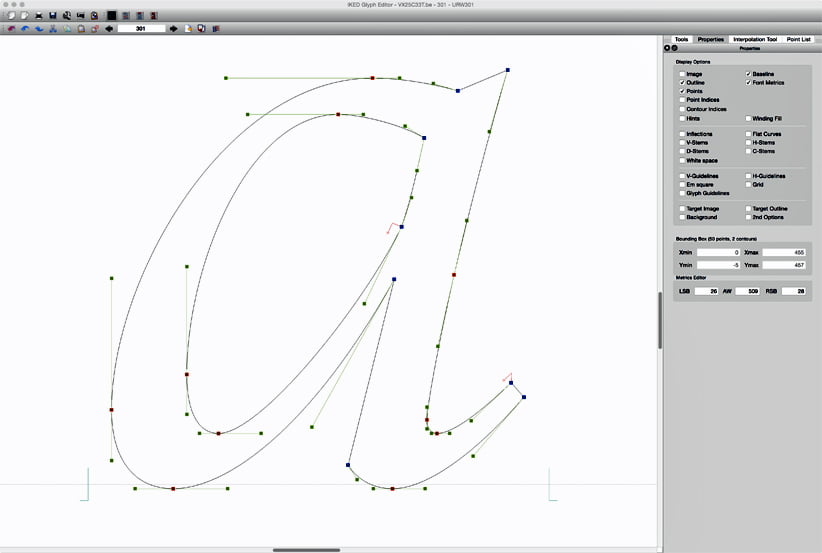  dtl Valiance is geschikt voor iedere denkbare typografische toepassing: van tijdschriftvormgeving tot website-ontwerp en van boektypografie tot huisstijlontwikkeling. Dit unieke lettertype kan worden toegepast door ontwerpbureaus en in kantooromgevingen. Haar klassieke, tijdloze, stevige doch elegante ontwerp maken dtl Valiance erg geschikt voor gebruik op hoge resolutie, zoals laserbelichters, maar ook voor apparatuur met een relatief lage resolutie, zoals computerschermen en laserprinters. De karaktersets die dtl Valiance ondersteunt, omvatten alle West-, Oost-, en Centraal-Europese talen, naast Cyrillisch (inclusief Bulgaarse en Servische varianten).
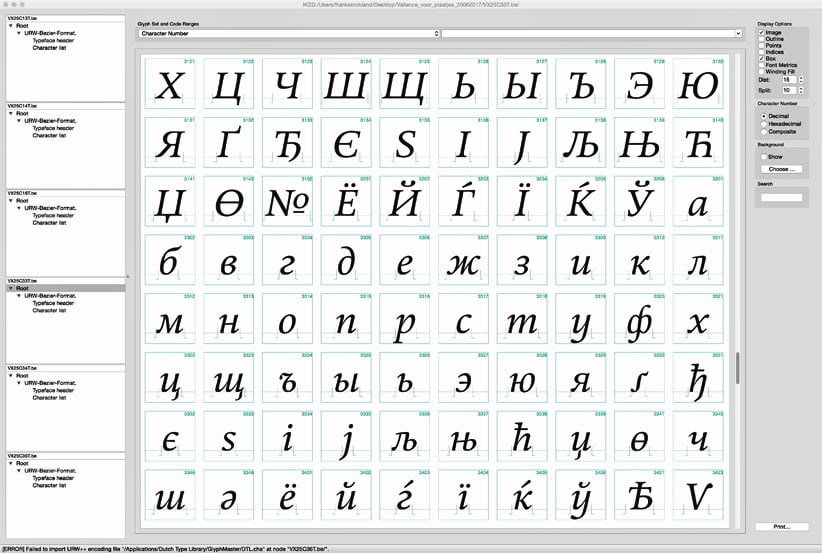
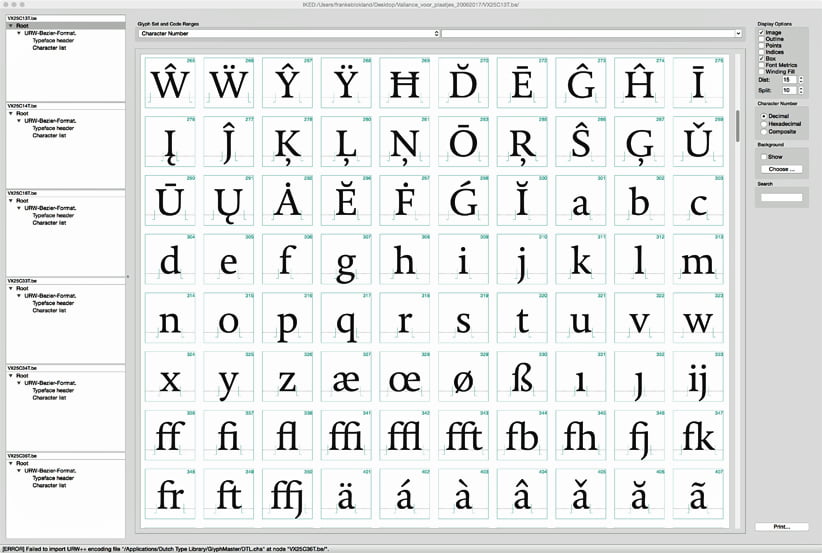  Speciaal voor de goody bag van de ATypI Amsterdam conferentie in 2013 publiceerde de Dutch Type Library Notes on the Design of dtl Valiance Cyrillic. In dit boekje presenteert Hanna Hakala een verzameling van aantekeningen die zij maakte tijdens het ontwerpproces van dtl Valiance. Deze beknopte publicatie voorziet letterontwerpers met duidelijke richtlijnen voor het ontwerpen van Cyrillische karakters en bevat verder historische achtergrondinformatie. Vier jaar geleden waren de reacties op Notes on the Design of dtl Valiance Cyrillic erg positief, zoals deze van een manager van ’s werelds grootste fontdistributeur: ‘You produced an excellence type specimen and story on Cyrillic letterforms. It is wonderfully done, and a true pleasure to read and absorb.’
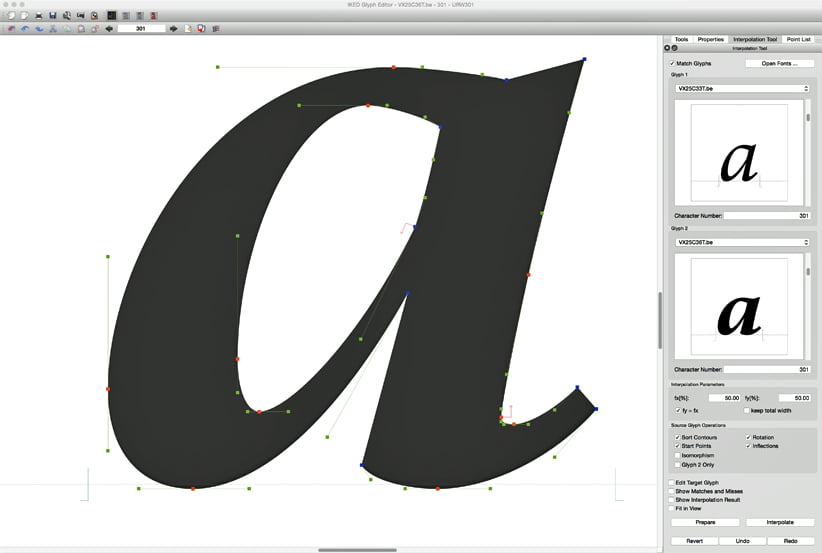
Bovenop al deze functionaliteit komt de optie om OpenType Layout features files (met afdko syntax) te im- en exporteren. Bij het importeren vindt subsetting plaats, wat inhoudt dat features die niet overeenkomen met de karakterset van een font worden verwijderd. Dit is mogelijk doordat de programmeurs van urw++ de functionaliteit van de afdko hebben uitgebreid.
dtl OTMaster is verkrijgbaar voor Mac os X –versie 6 is volledig geoptimaliseerd voor Retina– Windows, en Linux. Alle downloads bevatten de otm handleiding in pdf formaat. Een gebruikerslicentie voor otm 6 kost normaal € 255,– maar wordt tot 1 juni 2016 geleverd met 25% korting, oftewel €191,25 via dtl’s FontTools Shop. Gratis ‘Light’ (3.6) versies zijn te downloaden van de FontMaster website.   Op 6 februari 2007 verschenen zes regionale kranten van uitgeverij Wegener voor het eerst in tabloid formaat (zie ook dit nieuws. Een zevende editie werd sinds eind 2006 al gedrukt op het kleinere formaat. De overgang verliep technisch soepel op het Hermes opmaaksysteem en de nieuwe tabloids werden overwegend positief ontvangen.
Voorafgaand aan de omzetting naar tabloid formaat hadden grafisch ontwerpers van Wegener, merkendeskundigen en lettertypenexperts van de Dutch Type Library meer dan een jaar samengewerkt om de vormgeving van de zeven edities te vernieuwen. Tezamen vormen deze edities met zo’n miljoen tabloids per dag één van de grootste kranten in de wereld en daardoor heeft de vormgeving ervan behoorlijk wat impact. Alle toegepaste lettertypen werden ontwikkeld door de Dutch Type Library. De nieuwe lettertypen werden speciaal ontwikkeld voor toepassing in kranten: dtl Porta News werd ontworpen door de Kroatische letterontwerper Nikola Djurek, en dtl Caspari News en dtl Albertina Headline werden ontwikkeld door de dtl Studio. Voor sommige redactionele stukken werd dtl Albertina toegepast. Voorafgaand aan het herontwerp vonden verschillende intensieve leesbaarheidsonderzoeken onder groepen lezers plaats. De uitkomst was een klare overwinning van dtl Porta op Swift, het lettertype dat totdantoe het meest was toepast door uitgeverij Wegener. dtl’s oprichter Frank E. Bloklend ontwierp de zeven nieuwe krantentitels. Uitgangspunt daarbij was de standaardisatie, modernisering en technische verbetering van de bestaande krantentitels, zonder dat de indentiteit te veel werd veranderd. Dat laatse was een voorwaarde van uitgeverij Wegener, dat daarmee tegemoetkwam aan de voorkeuren van de ‘lokale’ redacteuren en journalisten. In 2012 werd het ontwerp van de Wegener-dagbladen nog verder geoptimaliseerd. Een special daartoe gevormde werkgroep, geleid door grafisch ontwerper Erik Gigengack en geadviseerd door krantenspecialist Mark Porter werkte in totaal zo’n driekwart van een jaar hieraan. Toentertijd waren dtl Caspari News en dtl Porta News al in gebruik, zoals hierboven gememoreerd, maar met beperkte sets van stijlen en gewichten voor de lopende tekst en kleinformaat koppen. Beide lettertypen werden uitgebreid met additionele fonts voor tekstformaat én met geheel nieuwe displayversies, die ind plaats kwamen van de dtl Albertina en dtl Albertina Headline fonts. Sommige van de nieuwe fonts worden nu ook door uitgeverij Wegener op het web toegepast in @font-face formaat. De eerste reacties van lezers en producenten van de Wegener-dagbladen op de nieuwe dtl ‘News’ lettertypen zijn erg enthousiast. De complete serie van dtl Caspari News en dtl Porta News fonts zijn nu ook beschikbaar voor de eindgebruikersmarkt en verkrijgbaar via dtl’s webwinkels. Een speciale letterproef op tabloidformaat, die oorspronkelijk geproduceerd was voor de goody bag van de ATypI Amsterdam 2013 conferentie, is op aanvraag verkrijgbaar bij de Dutch Type Library.    Op zaterdagavond 12 oktober 2013 vond het diner van de ATypI conferentie plaats in het sfeervolle Winter Garden restaurant van Grand Hotel Krasnapolsky in Amsterdam. Meer dan 300 conferentiegangers genoten van het uitstekend verzorgde buffet, dat was gesponsord door Adobe. Het hoogtepunt van de avond was de presentatie van de derde Dr. Peter Karow Award for Font Technology & Digital Typography (kortweg pka) aan Dr. Donald E. Knuth.
Grand Hotel Krasnapolsky in Amsterdam
Bij de ingang van het Winter Garden restaurant ontving iedereen een aandenken in de vorm van een 56 pagina’s dik boekje met als titel Digital Typography & Artificial Intelligence. Hierin beschrijft software-pionier Dr. Peter Karow, oprichter van het bedrijf urw Software & Type GmbH begin jaren zeventig en vooral bekend én beroemd vanwege het ikarus formaat, hoe digitale typografie het letterontwerpen en tekst-layout heeft beïnvloed. Het heeft de productie van fonts en het zetten van tekst compleet veranderd.
Dr. Knuth kreeg een staande ovatie van het ATypI-publiek. En zoals Nicole Miñoza schrijft op Adobes typeblog: ‘Het was een popsterrenmoment passend bij Dr. Knuths briljante carrière en significante samenwerkingen. De auteur van het monumentale, uit meerdere delen bestaande Art of Computer Programming liet de zaal hard lachen toen hij met een glinstering in de ogen dit werk aanprees. Dr. Knuth omarmde het publiek toen toen hij stelde dat hij het geweldig vond om oude vrienden op de conferentie te ontmoeten, maar dat het bovenal inspirerend was om zoveel jonge creatieve mensen te zien die de volgende generatie vertegenwoordigen.’